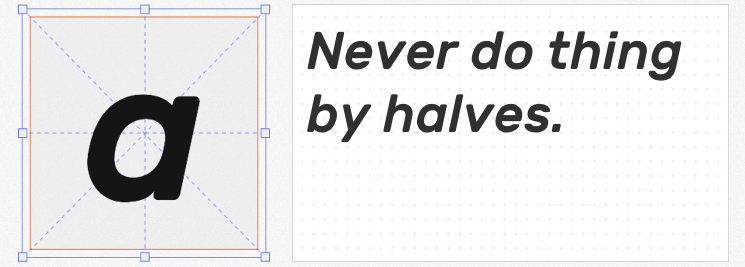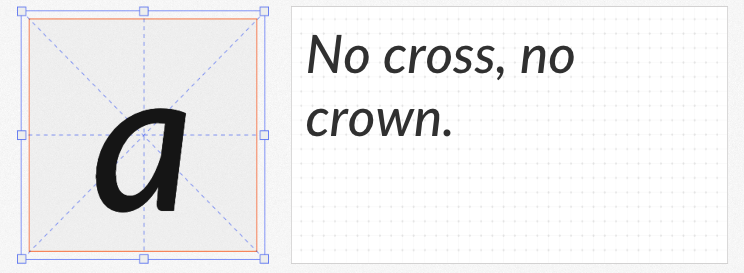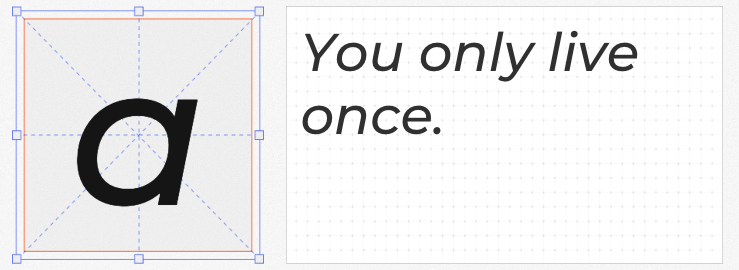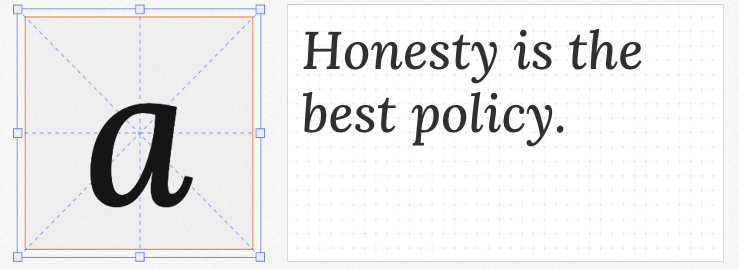
在视觉设计中,斜体英文字体是强化动态感、营造视觉张力的秘密武器。本文精选四款免费可商用的斜体英文字体,它们兼具美学价值与实用性能,能轻松适配品牌设计、海报标题、数字媒体等多元场景。
作为Google Fonts平台上的明星字体,Rubik Medium Italic以开源无衬线设计打破传统限制。其12°倾斜角度经过精密计算,既保持文字可读性,又赋予动态韵律。字体笔画采用模块化拼接技术,体现几何美学的极致追求。
这款以南美蒙特塞拉特岛命名的字体,将建筑线条的硬朗与海洋元素的流动完美融合。8°倾斜设计配合1.2:1的宽高比,使"G"字母的环形结构与"M"字母的锯齿边缘形成独特视觉对话。在旅游品牌VI设计中,其略带手写感的笔触转折(如"a"字母的开放尾端),能自然传递度假场景的轻松氛围。
作为少有的免费衬线斜体,Lora Medium Italic通过18°大角度倾斜重构书法美学。其"Q"字母的螺旋尾饰与"g"字母的双层结构,完整保留了钢笔书写的压力变化轨迹。在文学杂志封面设计中,该字体0.8mm的衬线高度与0.3mm的笔画粗细对比,既能营造古典氛围,又通过数字优化确保屏幕显示的清晰度。
这款波兰设计师创作的字体,将季节温度转化为视觉语言。10°温和倾斜配合圆角处理技术,使"e"字母的开口弧度与"n"字母的转角圆润度达到完美平衡。使用在儿童品牌包装设计中,能自然的传递温暖亲和的品牌气质。
四款字体通过精准的倾斜角度控制、文化元素的创意转化与数字技术的深度融合,重新定义了免费商用字体的设计标杆。它们不仅降低设计成本,更以开放授权模式激发全球创意者的无限可能。